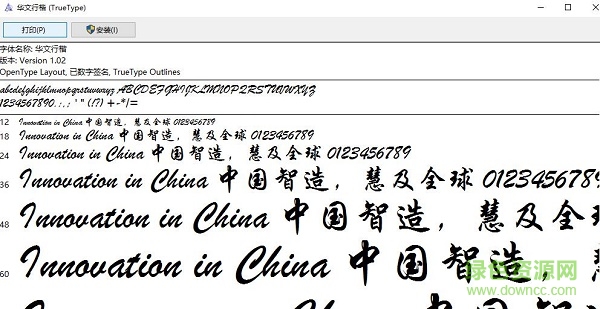
stxingkai是什么字體?stxingkai 字體又叫華文行楷字體,筆畫靈活,線條流暢,字形優(yōu)美,結(jié)構(gòu)穩(wěn)定,實(shí)用性與藝術(shù)性結(jié)合完美,需要的朋友快來(lái)下載吧!
行楷的用筆則靈活、方便,一般不需要逆鋒、頓筆、停筆等嚴(yán)格的運(yùn)筆,不強(qiáng)調(diào)用筆中更多的提按、筆畫形態(tài),只要求筆道流暢,使轉(zhuǎn)合理,行筆巧妙。還可以依照書寫者的習(xí)慣而使筆畫的行筆出現(xiàn)各種變化,甚至依照個(gè)人不同的審美和書寫風(fēng)格去追求或創(chuàng)造出不同的筆道線條。